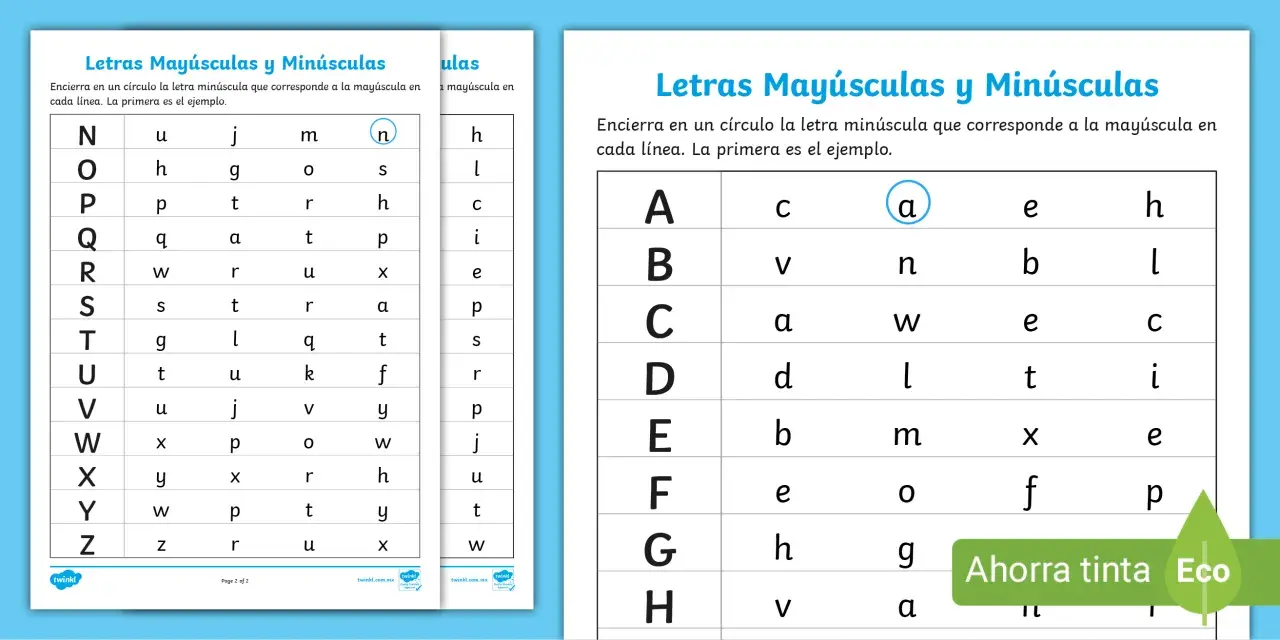
La Y mayúscula en tipografía y lettering - guía práctica
La mayúscula de la letra Y parece simple, pero en cuanto la sacas de una línea de texto y la llevas a un cartel, una portada o una composición decorativa, empieza a exigir decisiones muy concretas. Aquí explico cómo se construye, en qué contextos se usa, qué estilos tipográficos le favorecen y qué errores conviene evitar si quieres que se vea limpia, equilibrada y legible.
Lo esencial para trabajar la Y con criterio visual
• Forma: suele combinar un eje central con dos brazos superiores, aunque cada fuente la resuelve de forma distinta.
• Uso: en español funciona como cualquier otra mayúscula al inicio de nombres propios, después de punto y en siglas o títulos cuando corresponde.
• Diseño: en serif gana presencia; en sans serif gana limpieza; en lettering depende mucho del contraste y del espacio negativo.
• Manual: el fallo más habitual es desequilibrar los brazos o cerrar demasiado la parte superior.
• Decoración: una Y grande funciona bien como inicial protagonista, pero necesita aire alrededor para no perder legibilidad.
Cómo es la Y mayúscula y por qué se reconoce tan rápido
En tipografía, a las mayúsculas también se las llama versales, y la Y pertenece a ese grupo de letras que ordenan una palabra antes incluso de leerla completa. Yo la veo como una letra puente: puede ser sobria, geométrica o muy expresiva, pero siempre necesita equilibrio entre sus brazos superiores y la base para no parecer vencida hacia un lado.
Como explica Letter Fountain, las mayúsculas derivan de formas romanas pensadas para grabarse, y esa herencia todavía se nota en la claridad estructural de la Y. En muchas familias tipográficas aparece con un tronco principal y dos brazos que abren hacia arriba; en otras, el dibujo es más angular, más suave o más ornamental, pero la lógica sigue siendo la misma: una forma que debe leerse con rapidez y sostener el ritmo del conjunto.
Esa anatomía hace que la Y se note mucho en acrónimos, iniciales y titulares, donde una sola letra puede cambiar la impresión de toda la línea. Entender esa base formal ayuda a escribirla mejor, y justo ahí es donde empieza el trabajo a mano.
Cómo dibujarla a mano sin que pierda equilibrio
Cuando la trabajo a mano, no empiezo por los adornos sino por el esqueleto. La Y necesita un trazo principal claro y dos brazos que abran suficiente espacio arriba; si ese hueco se cierra demasiado, la letra pierde aire y se vuelve torpe. El espacio negativo, es decir, el hueco que rodea los trazos, es tan importante como la línea que dibujas.
En imprenta
En una versión de imprenta o rotulación sencilla, yo suelo partir de tres decisiones: anchura, inclinación y remates. Una Y demasiado estrecha parece frágil; una demasiado ancha se desordena. Si usas serifas, procura que los remates acompañen al resto de la familia tipográfica y no compitan con el trazo central.
• Marca primero el eje: te ayuda a no desplazar la letra hacia un lado.
• Abre los brazos con la misma intención: si uno cae más que el otro, la Y se desequilibra enseguida.
• No acortes demasiado la base: una parte inferior muy corta hace que la letra pierda presencia.
En cursiva y lettering
La cursiva introduce otra lógica: el trazo se vuelve continuo y la letra gana movimiento. Ahí funciona muy bien un pequeño contraste de presión, con una entrada más ligera y una salida algo más firme. En lettering con pincel o rotulador, ese contraste evita que la Y parezca una simple horquilla rígida.
• Deja respirar la parte superior: la Y necesita una apertura visible para no parecer comprimida.
• Controla el grosor: si engrosas demasiado los brazos, la letra pesa más de la cuenta.
• Revisa el resultado a distancia: si solo se entiende de cerca, la forma todavía no está cerrada del todo.
Cuando la estructura funciona, la letra empieza a comportarse bien en cualquier tamaño. Y eso nos lleva a un punto práctico: cuándo conviene ponerla en mayúscula dentro del texto y cuándo no.
Cuándo usarla en español y en piezas gráficas
La Y mayúscula no tiene un tratamiento especial frente al resto de versales: se usa cuando toca por norma o por jerarquía visual. Eso significa inicio de frase, nombres propios, siglas, rótulos, títulos y composiciones donde la capitalización forma parte del diseño. La RAE recuerda que las mayúsculas no eliminan la tilde cuando la palabra la necesita, así que la forma de la letra y la ortografía del conjunto son cosas distintas.
En nombres propios como Yolanda o Yago, la mayúscula va de forma natural. En cambio, en un texto corrido yo no la subo solo para que “se vea más bonita”. Si la palabra no lo pide, la capitalización forzada suele romper el tono del párrafo. En una portada, una cabecera o una marca personal sí puede funcionar como recurso de énfasis, siempre que no sacrifique legibilidad.